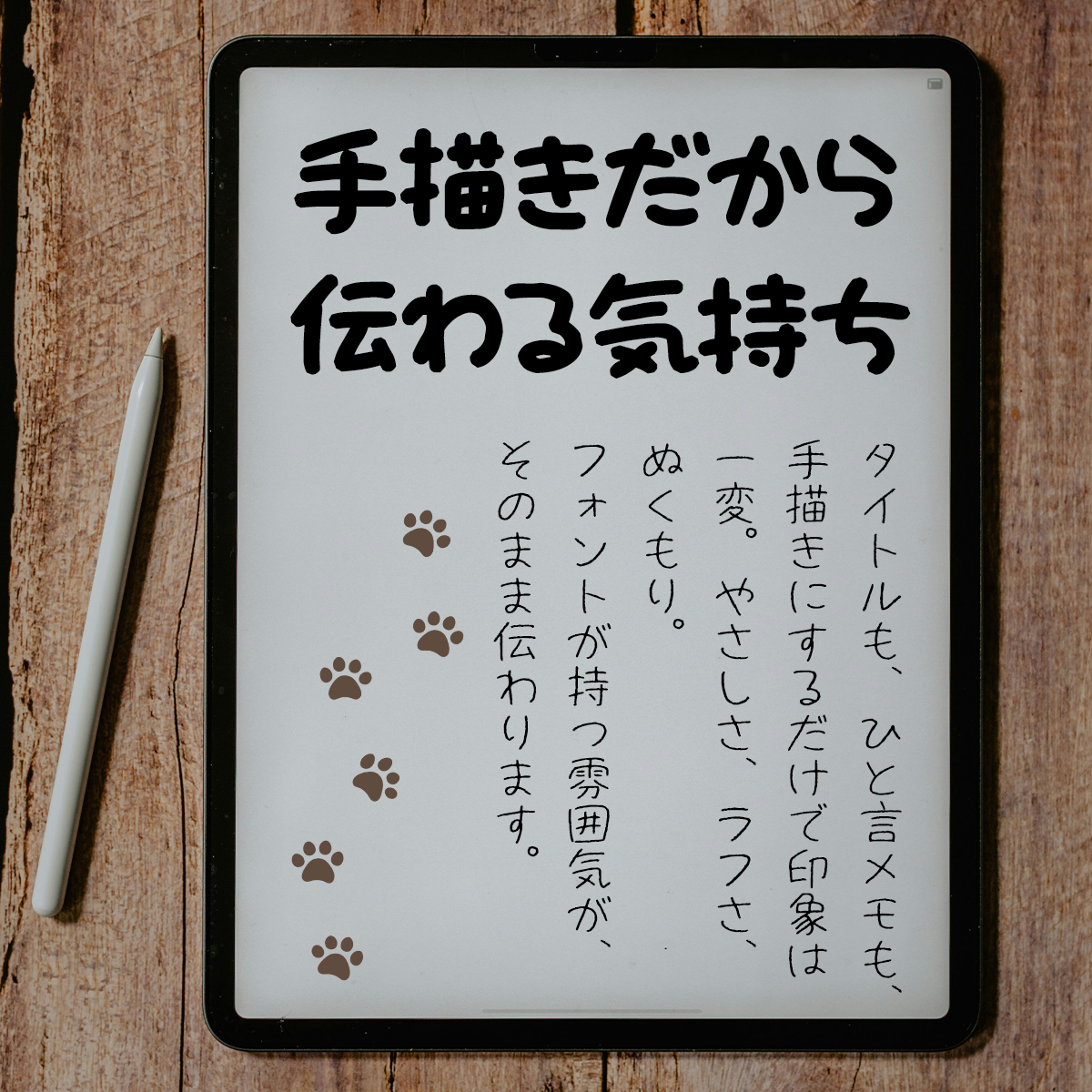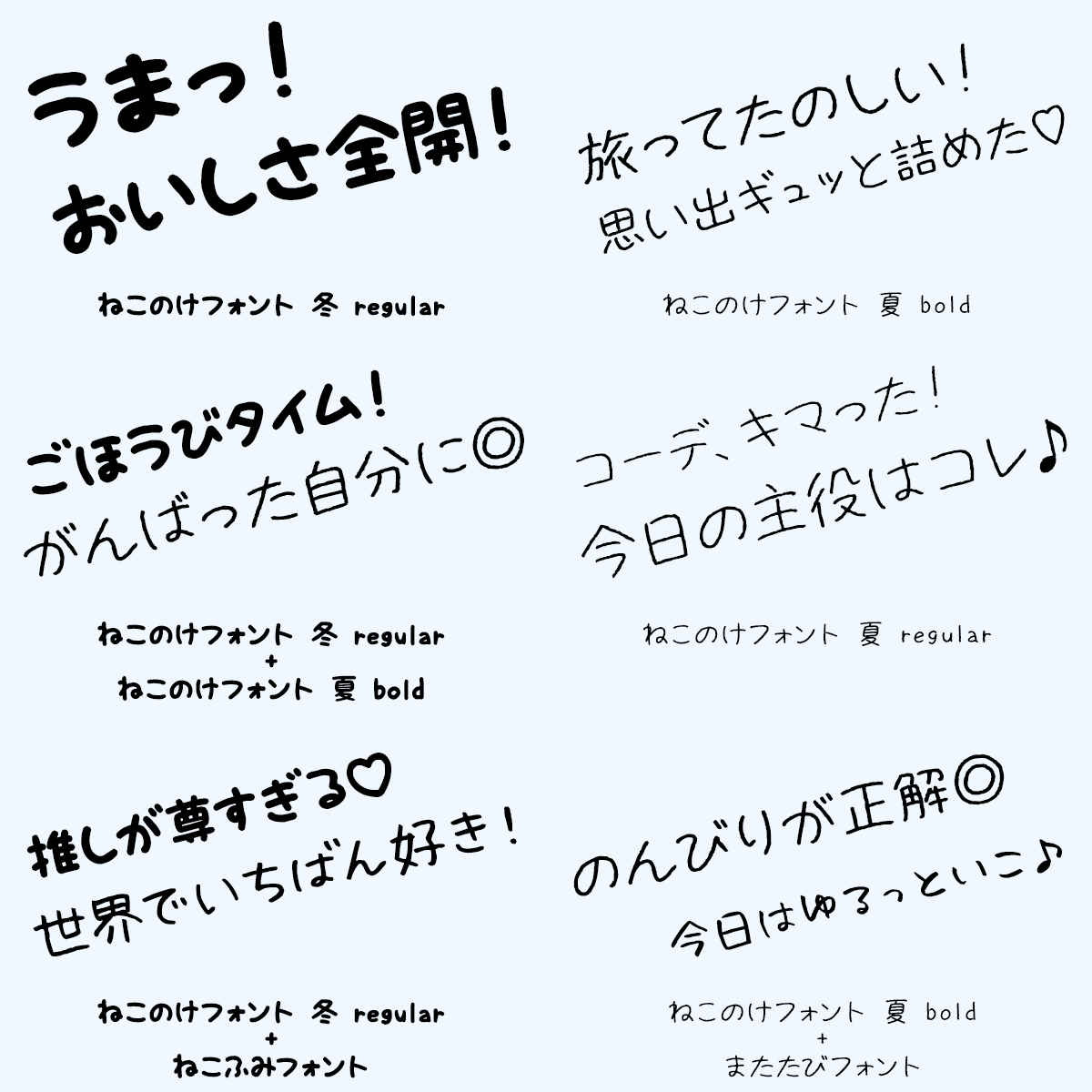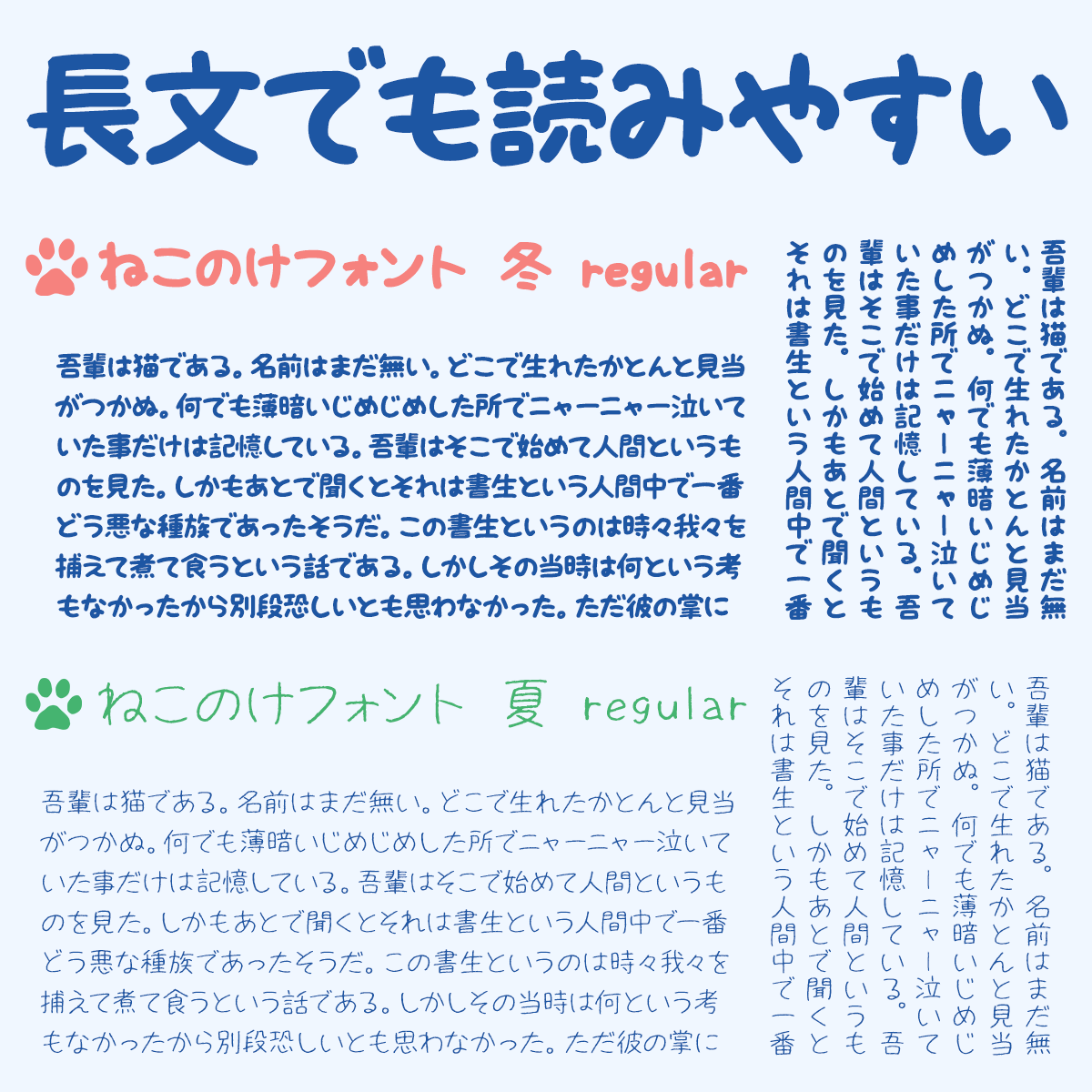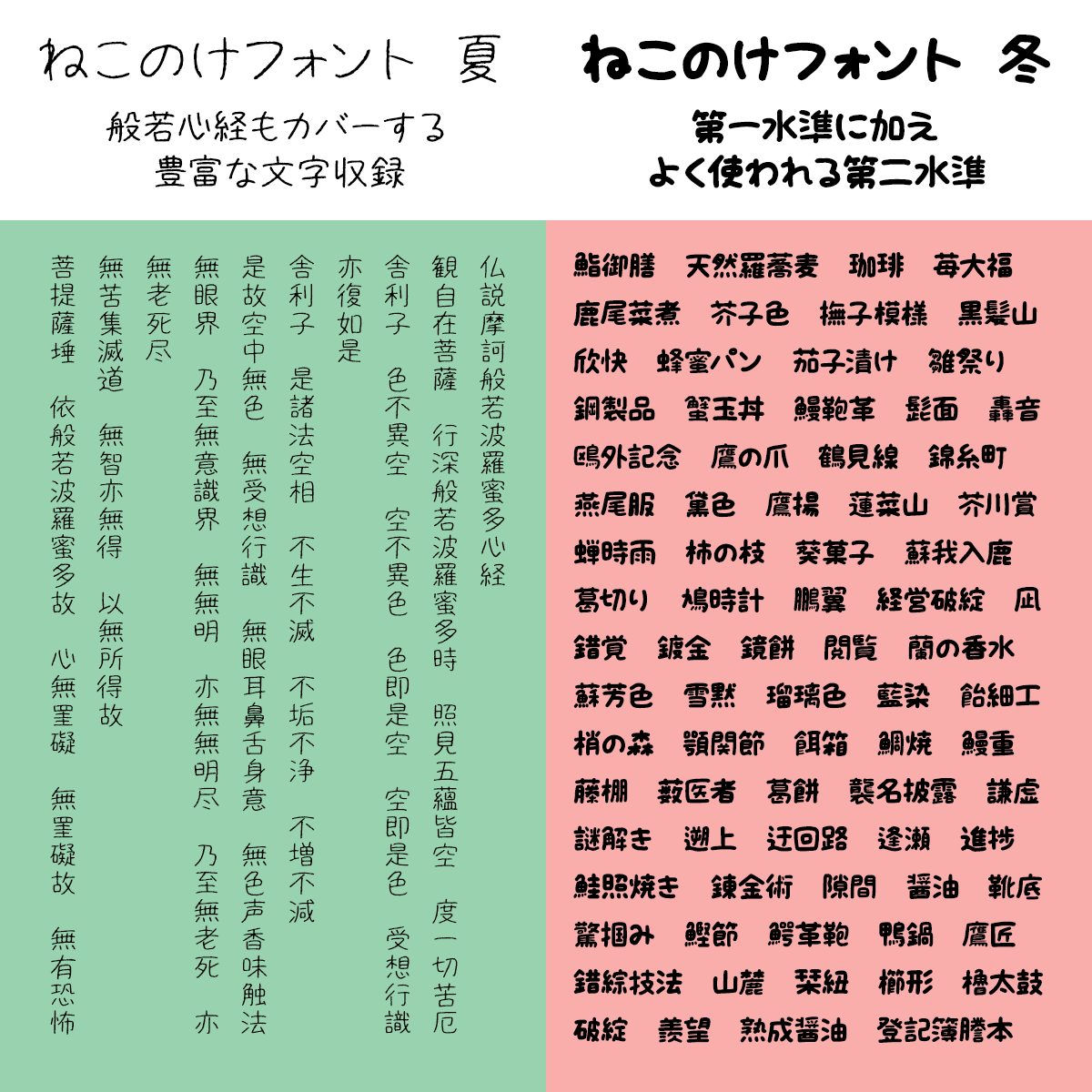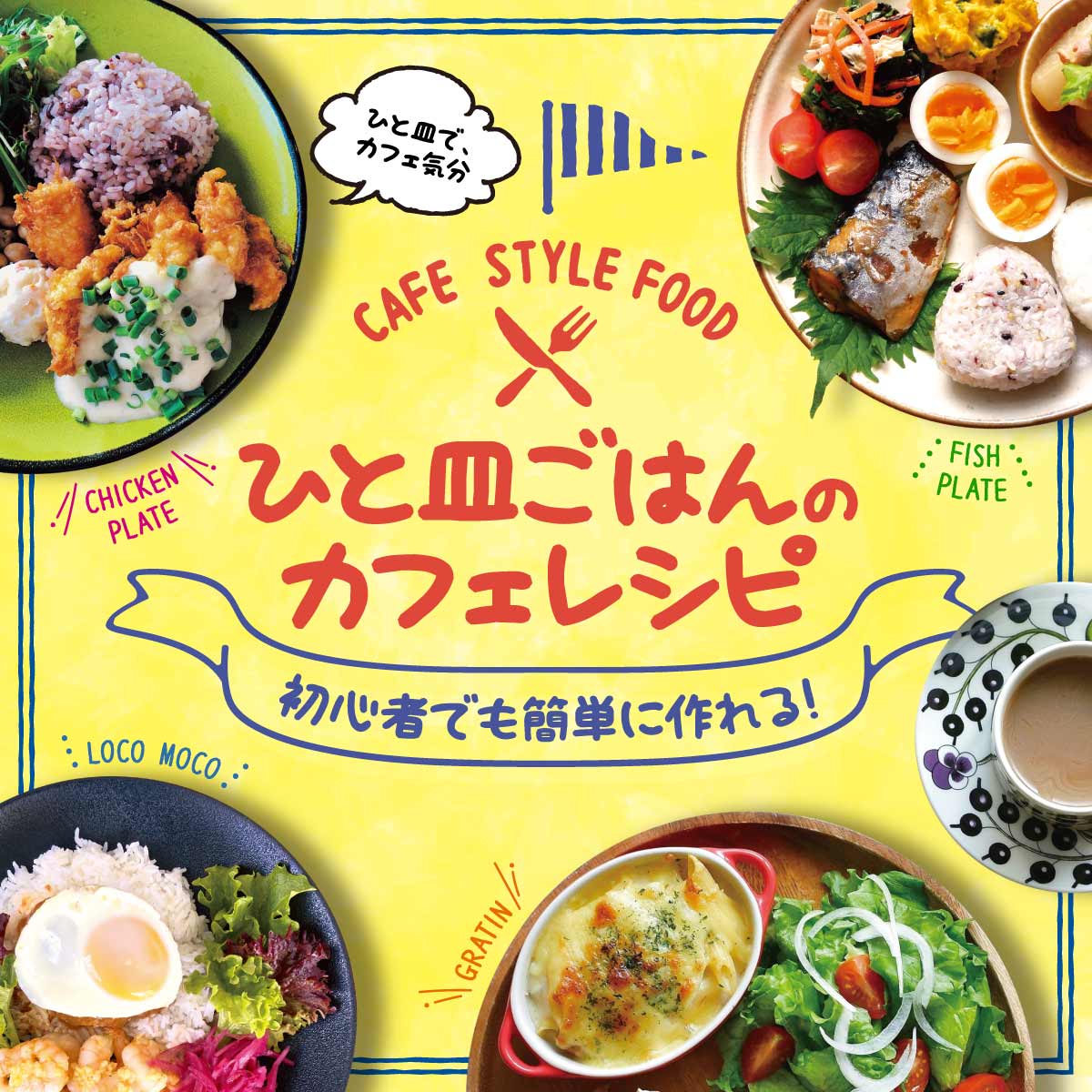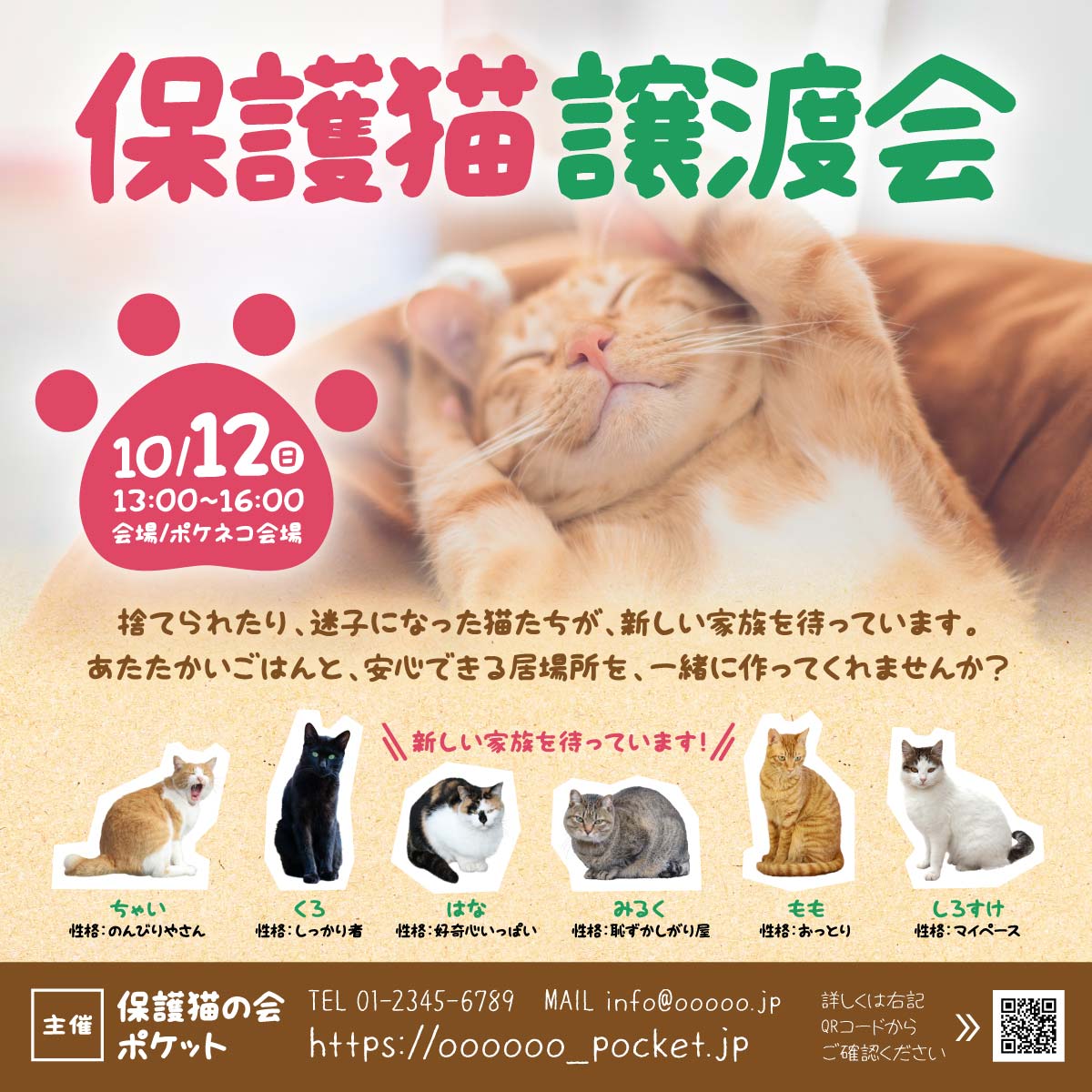
一つひとつ手描きで制作した手描きのリアル感「ねこのけフォント」
「ねこのけフォント」は、夏毛や冬毛が持つ印象をイメージして制作された手書き日本語フォントです。
夏毛は細く軽やかなタッチで透明感のある雰囲気を、冬毛は太くやわらかなタッチで安心感やぬくもりを感じさせます。どちらも全て手描きで作られており、フォントの自然な揺らぎと人の手による温度感が魅力です。
「ねこのけフォント」の概要
ねこのけフォント 夏 regular/bold
ねこのけフォント 冬
「ねこのけフォント」とは?
「字がかわいいね」から始まった、フォント制作のストーリー
「ねこのけフォント」を手がけた作者ねこふみゆちこさんは、もともと自分の字に強い自信を持っていたわけではありません。全国津々浦々の“かわいい字”の人たちとの文通の中で現在のゆちこさんらしい文字が生まれました。
Instagramに投稿した手帳が「字がかわいい」と褒められたことをきっかけに、手書きフォント制作の世界へ足を踏み入れました。ZINE制作のおまけとして作ったフォントが経験となり、作品は少しずつ形になっていきます。
プロデューサーとの出会いで制作の幅が広がり、三作目となる「ねこのけフォント(夏・冬)」が誕生。そこには試行錯誤と楽しさ、そして新たな挑戦への展望が込められています。
ねこふみゆちこさんについて
字を書くことと猫が好きな人。床で文字を書くことが多く、通りすがりの猫に紙を踏まれることから「ねこふみフォント」という名のフォントを作る。
元々はただの「ゆちこ」だったが、ついでに「ねこふみ」を苗字にもした。
SNSでは手帳やノートの写真を公開している。カリカリした書き心地のニードルタイプのボールペンが好き。
フォント制作のきっかけと最初の一歩
<Instagramに公開したゆちこさんの「手帳の中身」>
Instagramが始まりの場所
Instagramを始めた頃に「手帳の中身」を公開するハッシュタグを見つけて、人の手帳を見るのが楽しくて夢中になりました。
自分の手帳も投稿してみたら「字がかわいい」と褒めてもらえて、嬉しかったのが最初のきっかけです。
フォント制作との出会い
その後、しばらくして武蔵システムさんの「手書きでフォント」というソフトを知り、「そんなに簡単に作れるんだ」「じゃあ作ってみよう」と思ったのが、実際にフォント制作を始めた理由です。
最初の失敗と学び
最初に作ったフォントは、幅や大きさを揃える必要があることを知らず、漢字練習帳に書くような感覚で自由に書いたら、バランスがガタガタなフォントになってしまいました。(このフォントは現在非公開)
ZINE制作から生まれた一作目
<きっかけとなった「文字について」をテーマにしたZINE>
その後しばらくはソフトごと存在を忘れていたんですが、当時やっていたWEBSHOPで「文字について」をテーマにしたZINEを作ることにした時に、「おまけとして実際に使える手書きフォントを付けたら面白いのでは?」と思い立ち、書き上げたフォントが、一作目である「ねこふみフォント」の原型です。(このフォントも現在非公開)
今の字につながった原点と影響 ─ 手書き文字について
<ゆちこさんらしさを保持して筆ペンで制作したまたたびフォント>
子どもの頃の文字への思い
小学生の頃も中学生の頃も、特に特徴のない文字を書いていました。
母が誰からも「達筆」と言われる字の人で、「お母さん、字上手いね」とよく言われていたので、自分も大人になったら自然と字が上手くなるんだろうなと漠然と思っていたんです。でも、そんなわけもなく。
達筆とは程遠いまま大人になり、習字は全然ダメで今も苦手です。
(※ちなみに「またたびフォント」は筆ペンで書いたフォントですが、ただの酔っ払いのへろへろ文字です)
高校時代の文通が転機に
そんな私が(上手くはありませんが)褒めてもらえるような今の字になったきっかけは高校時代の文通でした。
当時は今でいう「推し」を語る手段が現地か文通くらいしかなく、一番多い時で20人くらいと文通していたと思います。
全国の“かわいい字”から学んだこと
その中で出会った全国津々浦々の“かわいい字”の人たちの文字をあれこれ真似するうちに、今の自分の字が完成しました。
「ねこのけフォント」誕生の裏側
<アナログで太字フォントを作ろうとしてた時の残骸>
ねこふみ、またたびに続く三作目の挑戦へ
「ねこのけフォント」は三作目の手書きフォントです。
最初は「サインペンで書いた普通の文字の『ねこふみフォント』」、次に「筆ペンで書いたへろへろ文字の『またたびフォント』」ときて、プロデューサー(ゆるてがきこむ管理人さん)から「次は太字を作ってみませんか?」と提案されました。
太字制作と半デジタルへの移行
<半デジタルで制作したねこのけフォント冬の作業風景>
太めのペンを買って試してみたもののアナログには限界を感じ、この頃から半デジタルに移行することにしました。
デジタルで書いてみると意外に楽しくて、「細字の夏毛と太字の冬毛、2種類にするのはどうですか?」と逆にこちらから提案したのが始まりです。
夏毛と冬毛、それぞれの制作過程
ねこのけフォント 夏 冬 手書きフォント これ本当に第一水準?というような難解漢字
<これ本当に第一水準?というような難解漢字>
(夏)はさくさく書ける文字にしたかったので、作業も楽しかった記憶があります。
一方、(冬)はデジタルのみで作ったんですが、本当に大変でした。
「とりあえず漢字は第一水準まで」と決めていたものの、「これ本当に第一水準?」と思うような難しい漢字もあって……。
線が潰れないように、でもバランスがおかしくならないように、と試行錯誤を繰り返していました。
プロデューサーとの出会いとフォント制作の広がり
<ゆちこさんを感動させるプロデューサーが制作する紹介画像>
憧れの人とのつながり
私にイラストのお仕事を依頼してくださったのが出会いだったんですが、実はそれより何年も前に某ブログサイトで「この人のセンスいいなあ」と思いながら見ていた方でした。
だから「えっ、私でいいんですか?本当に?」と驚きましたし、憧れていた人からフォントについても「手書きフォント、もっと売り出してもいいと思います」と言ってもらえたのがすごく嬉しくて。
思わず「じゃあプロデュースしてくださいよ〜!」と伝えた結果、今につながっています。ほんと、言ってみるものですね……。
使用例デザインで実感する文字の魅力
フォントの紹介画像などはプロデューサーが作っているのですが、フォントが完成した瞬間よりも、使用例のデザインを見せてもらった時の方が感動が大きいです。
「すごい、これ私の文字なんだ……」と、ようやく実感が湧きます。
「ねこのけフォント」に込めた仕上げとお気に入りの文字
<それぞれに特徴がでている「ねこのけフォント」の記号たち>
仕上げの工夫と記号へのこだわり
(夏)は長文でもさらさら読めるように、(冬)は文字だけでも目立つように仕上げました。
気に入っている文字は記号なのですが、「♡」や「☆」はそれぞれに特徴が出ているかと。見てもらえると嬉しいです。
次に見据えるフォント制作への展望
<ゆるてがきこむの次回作にもぜひご期待ください>
「普通の文字」をデジタルで改めて形に
普通の文字、へろへろの文字、細字、太字と作ってきましたが、一周まわって今は「普通の文字を」「デジタル」で改めてフォント化したいと考えています。
まだ構想の段階ですが、すべてアナログで書いた「ねこふみフォント」の進化版のようなものを作れたらいいなと思っています。
「ねこのけフォント」の特徴
手描きのリアル感
ねこのけフォント 夏 冬 手書きフォント 手描きのリアル感
すべての文字を一つひとつ手描きで制作。自然な揺らぎや人の温もりがあり、デジタルながらも親しみやすい印象を与えます。
<ねこのけフォント 冬>